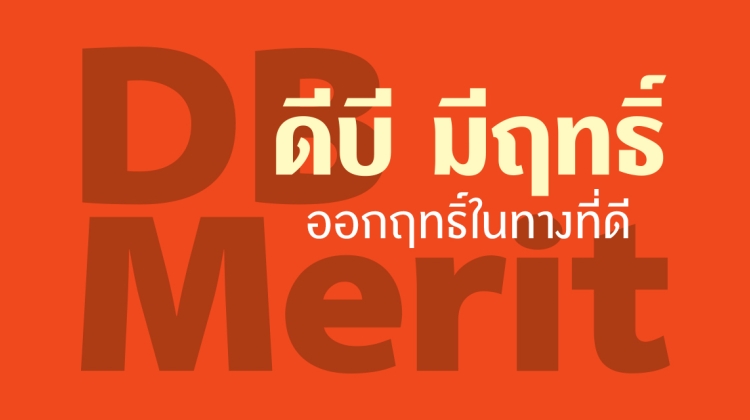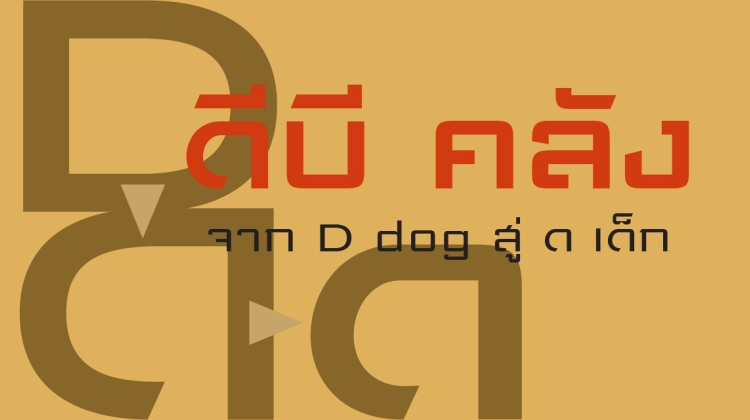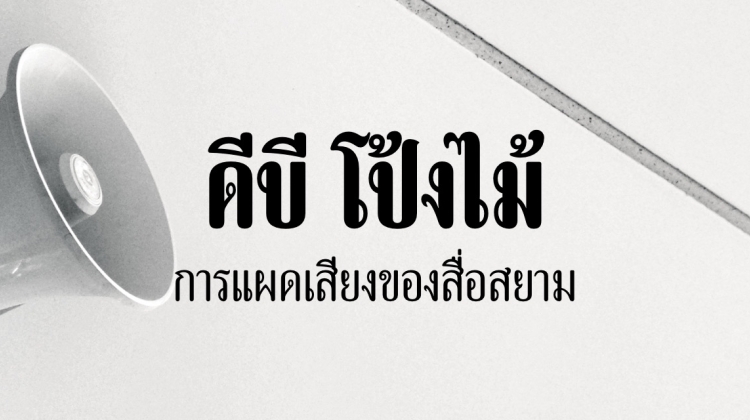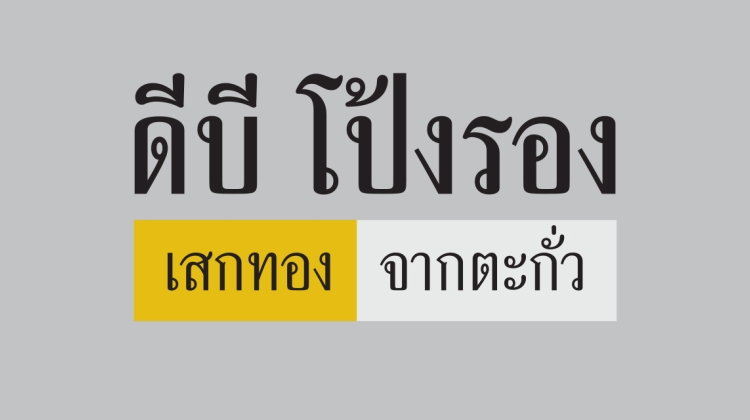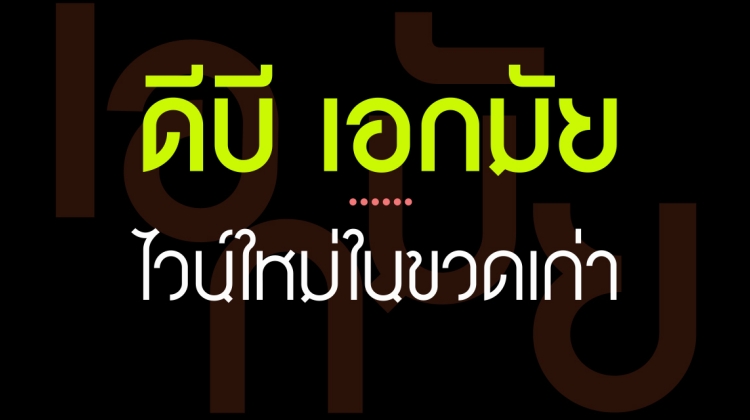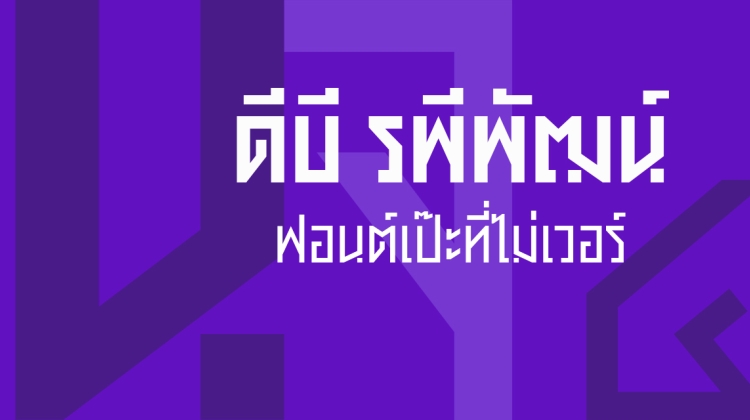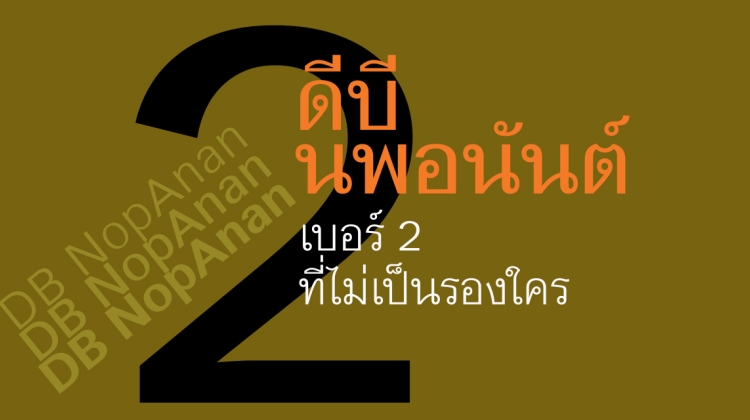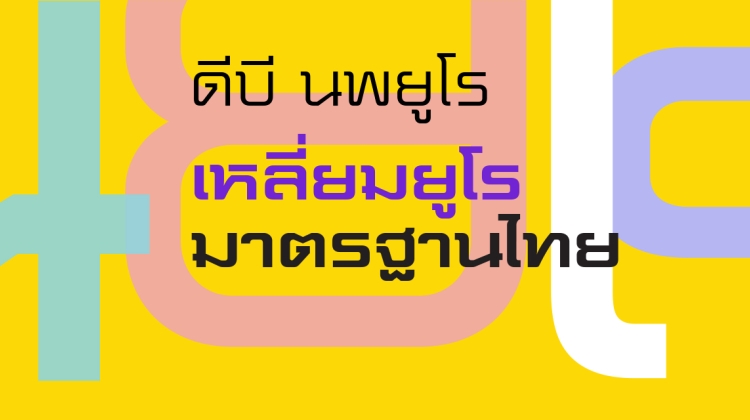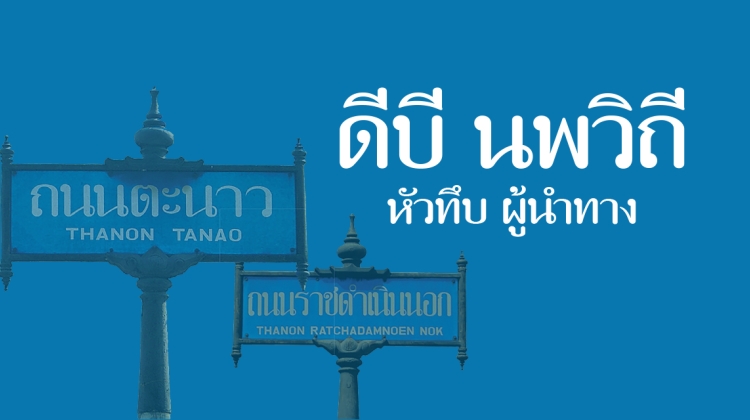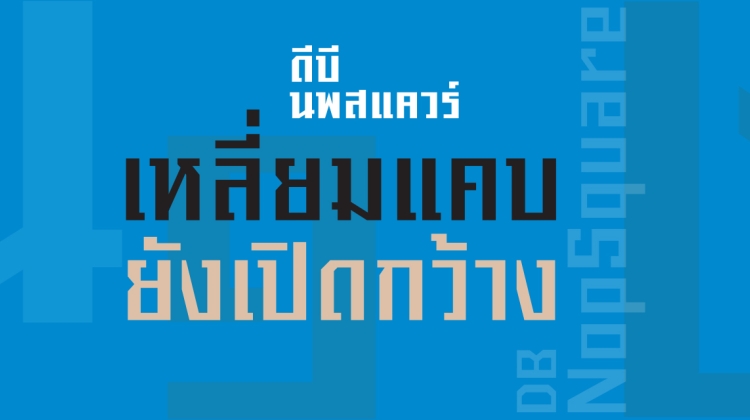
DB YangDung
เป็นฟอนต์ตัวแทนของแบบอักษรประดิษฐ์พาดหัวที่นิยมใช้ในอุตสาหกรรมภาพยนตร์ไทยในยุคอดีต
DB NopSquare
เป็นฟอนต์อนุรักษ์แบบตัวอักษรขูด ‘มานพ 1’ อักษรทรงเหลี่ยมแคบสำเร็จรูปพร้อมใช้ตัวแรกของไทย
DB NopVithee
เป็นฟอนต์เงาของแบบตัวอักษรเก่า ที่ใช้บนป้ายถนนใน กทม. มาช้านาน
DB NopEuro
คือฟอนต์ดิสเพลย์ไทย ทรงเหลี่ยมแบบ Eurostile สร้างจากแบบอักษรลอกไทย ที่ได้รับความนิยมอย่างสูงในยุค 70's
DB NopAnan
คือฟอนต์ใหม่ที่ทำเพิ่มเติมจากแบบอักษรลอก ‘มานพ 2’ อันเลื่องชื่อในอดีต
DB Mahachai
เป็นฟอนต์ไทยประเพณี ที่ได้จากการนำอักษรประดิษฐ์ ๑๒ ตัว บนปกหนังสือตำรากับข้าวโบราณมาปรุงรสใหม่
DB RapeePat
ฟอนต์ไทยทรงเหลี่ยม ที่ได้รับอิทธิพลมาจากตัวอักษรทำมือริมถนน
DB Ekkamai
ฟอนต์รูปทรงเรขาคณิตเส้นสม่ำเสมอ ที่ผ่านการบ่มเพาะด้วยกาลเวลา
DB PongRong
เป็นงานอนุรักษ์ฟอนต์ตัวโป้งทรงผอมยอดนิยมในยุคตัวเรียงพิมพ์ตะกั่วของไทย ให้กลับมาสุกใสเรืองรองอีกครั้ง
DB PongMai
จะแผดเสียงให้ดังอย่างไรบนพื้นที่กระดาษอันจำกัด? อักษรมีหัวตัวผอมเส้นทึบของ ‘โป้งไม้’ คือคำตอบในยุคทองของหนังสือพิมพ์สยาม
DB Clung
เป็นฟอนต์ไทยเสมือน Bank Gothic ฟอนต์ดิสเพลย์อักษรโรมันทรงเหลี่ยม ที่อายุเป็นเพียงแค่ตัวเลข
DB Merit
เป็นฟอนต์ดิสเพลย์ไทยเสมือนโรมันที่ซ่อนฤทธิ์ไว้ในรายละเอียดเพียงเล็กน้อย ทว่าสามารถออกฤทธิ์ได้เมื่อใช้ในขนาดใหญ่.